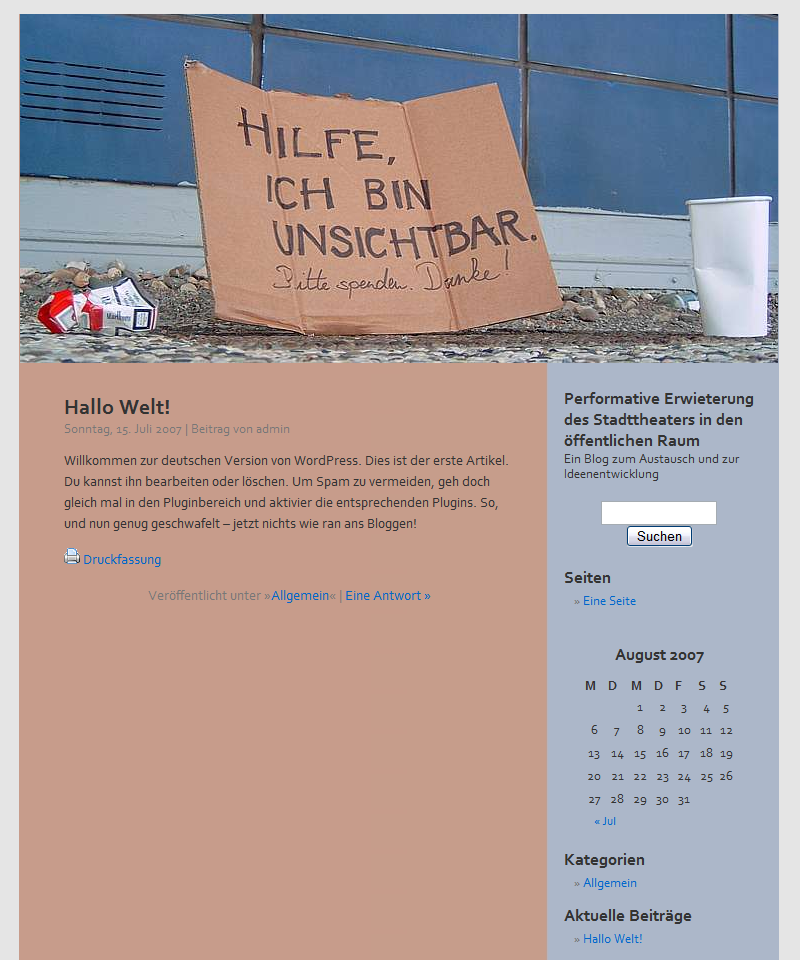
webseiten mit times in anwendung
ich bin auf der suche nach webseiten, auf denen die times new roman als fließtextschrift verwendet wird. ich weiß, sollte man nicht ... ich hänge aber gerade an der entscheidung, ein print-erscheinungsbild im web umzusetzen und eine serifenschrift würde halt einfach passen (ist ein schriftmix aus einer ziemlich modernen serifenlosen und der filosofia, was den print betrifft).
gibt es irgendjemand da draußen, der meine überlegung unterstützen würde oder höre ich ein lauthals gebrülltes und dreifach unterstrichenes: "NO!".
falls ja, würde mich interessieren, ob ihr seiten kennt, bei denen die times in guter lesbarkeit (web) zum einsatz kommt.
typografie.info ist für mich nämlich ein perfektes beispiel, da die georgia am mac hervorragend aussieht, am pc ... naja.
ok, sorry, mißverständlich ausgedrückt.
ich suche einfach ein paar "belege", dass seiten mit der times funktionieren. nicht irgendwelche seiten mit der times im einsatz. das screen-design steht soweit nämlich und ich würde es dem kunden gerne präsentieren. um für mich einfach aber mehr sicherheit zu haben, suche ich nach "guten" und "professionellen" seiten, welche die times verwenden. wenn es die nicht gibt, umso besser, dann eiere ich nämlich nicht länger rum. wäre dann zwar schade, ist aber so.
Nimm doch die Georgia und dieses Forum als Beleg dafür, dass es gut funktioniert. Die hat auch merh mit der Filosofia gemeinsam ...
ist schon in der "beleg"-sammlung :wink:
allerdings erscheint mir die georgia am pc/internet explorer zu kritisch, dachte daher, dass die times die zwischenlösung darstellt.
allerdings erscheint mir die georgia am pc/internet explorer zu kritisch
Was meinst Du mit kritisch? Im Gegensatz zur Times wurde die Georgia von Matthew Carter extra für die Verwendung am Bildschirm entworfen, sie stellt also in jedem Fall die bessere Lösung dar.
Viele Blogs verwenden heute übrigens auch die Georgia, was ziemlich schick aussieht. :)
allerdings erscheint mir die georgia am pc/internet explorer zu kritisch, dachte daher, dass die times die zwischenlösung darstellt.
:shock: Wie kommst Du denn darauf? :?: Nein, die Georgia ist klar die beste Lösung grade auch am PC, wenn es um »websichere« Schriften geht. Ich könne einige Websites die die Palatino erfolgreich einsetzten, doch das ist niemals so gut lesbar wie es mit der Georgia wäre.
allerdings erscheint mir die georgia am pc/internet explorer zu kritisch, dachte daher, dass die times die zwischenlösung darstellt.
Also ich bin mit der Georgia am PC mehr als zufrieden – Windows XP, Cleartype aktiviert, Browser Firefox 2 bzw. IE6 (Darstellung des Textes sind da aber identisch).
Eine klarere Darstellung einer Serifenschrift am Bildschirm bekommst du derzeit wahrscheinlich nicht, vielleicht noch mit den neuen C...-Schriften von Windows Vista.
Murkst der IE7 vielleicht daran rum? Den kenne ich nicht, irgendwas war da aber(?).
hast du mal ein Such-Beispiel? HTML-Quelltext lässt sich mit allen Attributen oder CSS in x-Varianten schreiben. Willst du nach Tags suchen oder nach ganzen Code-Passagen?
hast du mal ein Such-Beispiel?
Im Moment bräuchte ich für einen Artikel gerade dringend Webseiten, die schon auf Cleartype-Fonts setzen.
Such-String wäre als sowas wie "font-family: Calibri" oder "font face=Calibri".
Aber Google liefert da eben wie gesagt nur Webseiten, die entsprechende Quelltexte anzeigen, aber nie Webseiten, die diesen Kode tatsächlich zur Formatierung enthalten. Und die Dateiformat-Suche lässt gerade "html" oder "css" nicht zu. :evil:
Ich stand vor der gleichen Entscheidung wie Du. Ich dachte immer Arial, Verdana und Times wären websichere Schriften, musste mir aber sagen lassen nur Arial und Verdana wären es.
Dem liegen wohl nicht nur Mac und PC zu Grunde sondern auch Unix-Anwendungen.
danke auch an euch und eure einschätzung. ich selbst arbeite schon ewig nicht mehr am pc und bin eigentlich auch kein web-spezialist. wenn ich allerdings den typetester benutze (im IE 6 am pc), war mein eindruck bisher, dass der qualitätsunterschied (die darstellung betreffend) zwischen der georgia am mac und am pc größer ist als der bei der times.
mich hat das aber auch stutzig gemacht, als ich eben genannte blogs und insbesondere das typoforum abgeglichen habe, die alle die georgia einsetzen (und die wissen es ja am besten). also werde ich mal die einstellungen bei meiner alten krücke testen und mich wieder in meinen print-kram vertiefen, wo das alles ja keine rolle spielt :lol:
Es handelt sich um ein Wordpressblog mit nur leicht angepasstem Kubrick-Standard-Theme. Die Schriften-Reihenfolge sieht für ausnahmslos alle relevanten Elemente so aus:
font-family: Corbel, 'Lucida Grande', 'Lucinda Sans', Verdana, Sans-Serif;
Es hat nicht gestört, wenn man die Corbel nicht hatte, die Ersatzschriften erschienen eben relativ groß, aber das hat nichts kaputt gemacht.